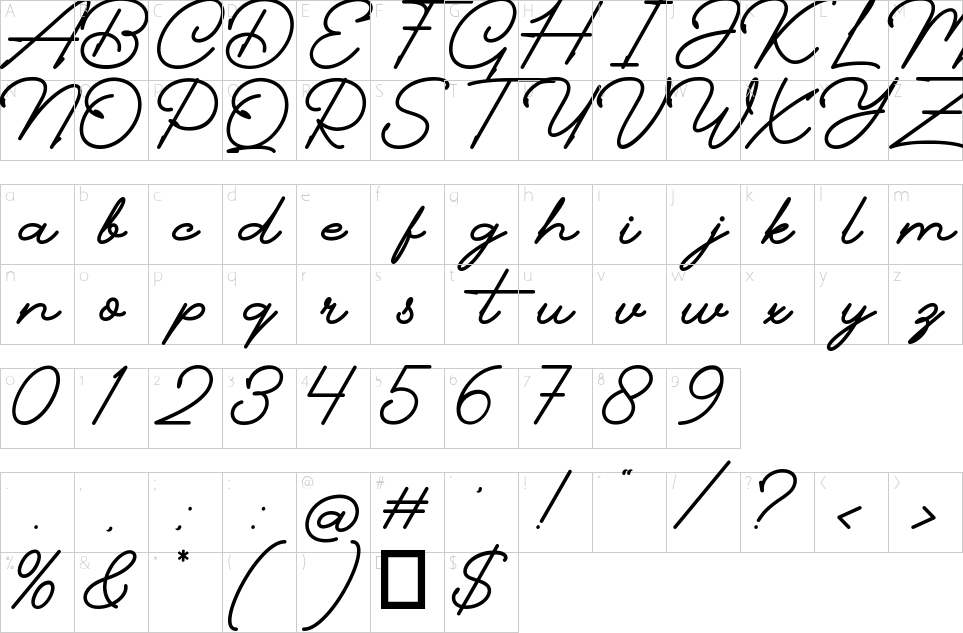
Descubra Jolfery Signature, uma elegante e sofisticada fonte de签字设计。Esta fonte foi cuidadosamente projetada pelo Naufal Labs, uma marca dedicada à criação de fontes de alta qualidade. Jolfery Signature é perfeito para designers que desejam dar um toque de sofisticação a seus projetos gráficos. Desenvolvida especialmente para os sistemas Windows e Mac, esta fonte é um presente de qualidade para qualquer designer que busque uma opção de fonte única e profissional. Com 1,064 downloads, é evidente que muitos designers já aprovaram Jolfery Signature. Experimente incorporar esta fonte em seus projetos e descubra por si mesmo o porquê dela ser um favorito entre os criadores de design.